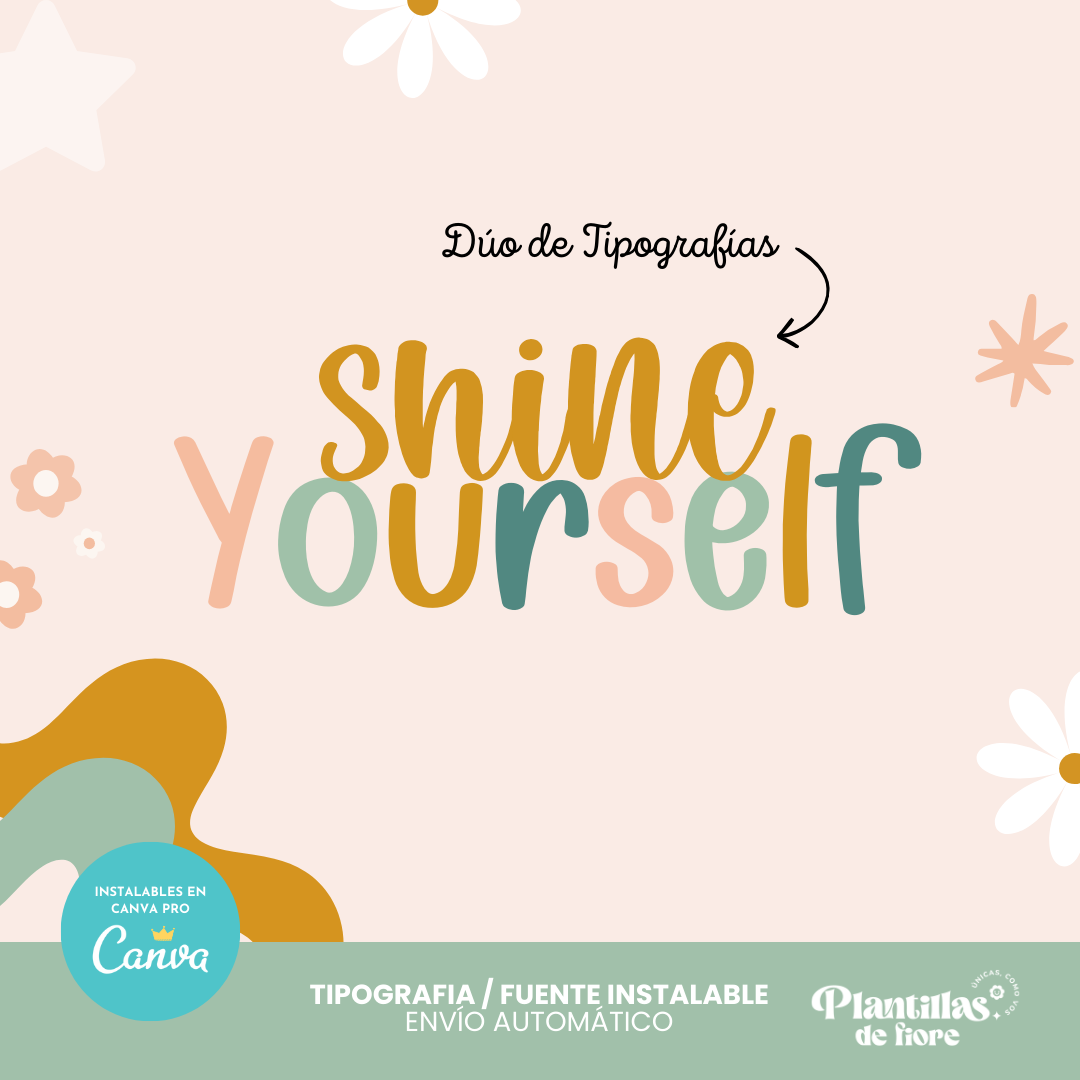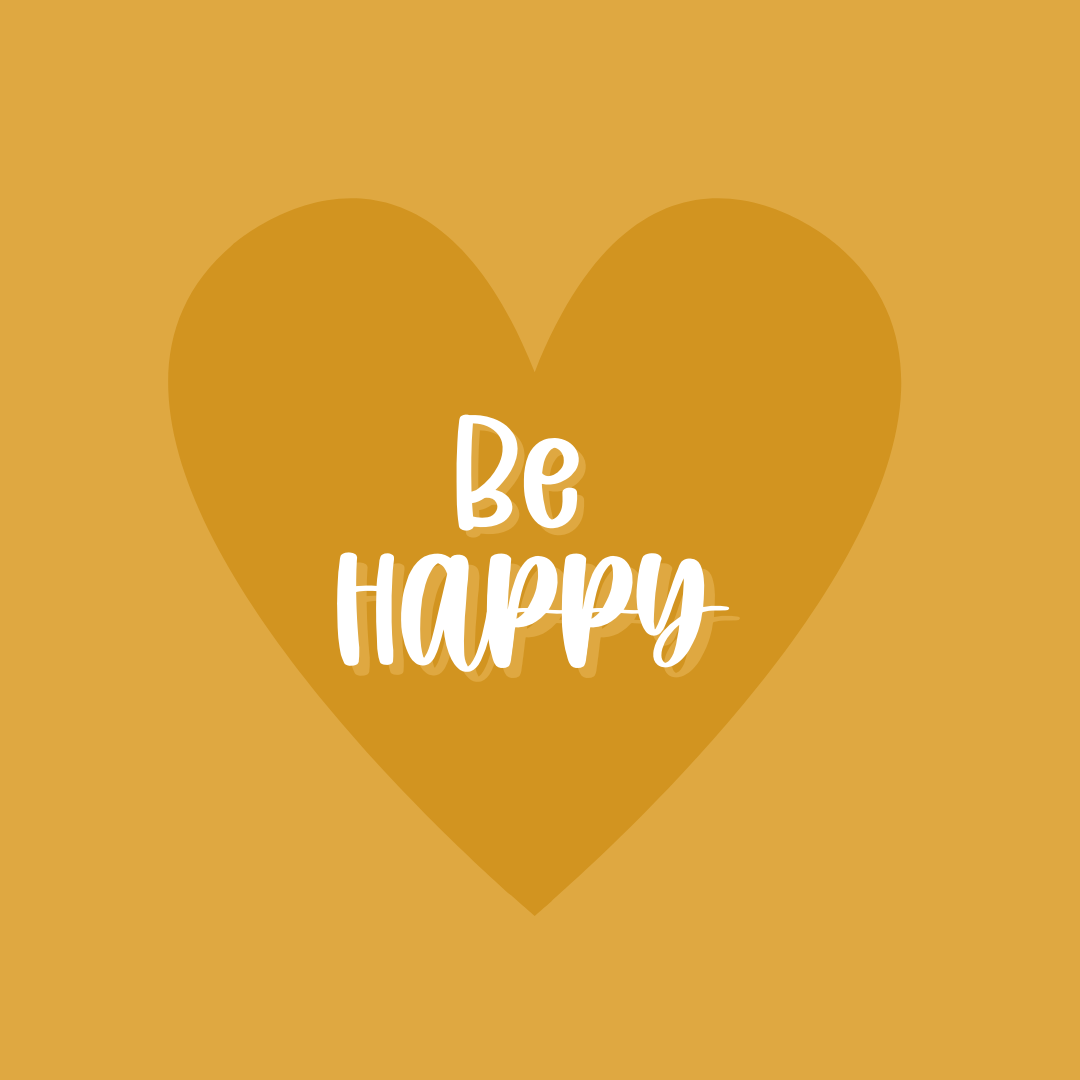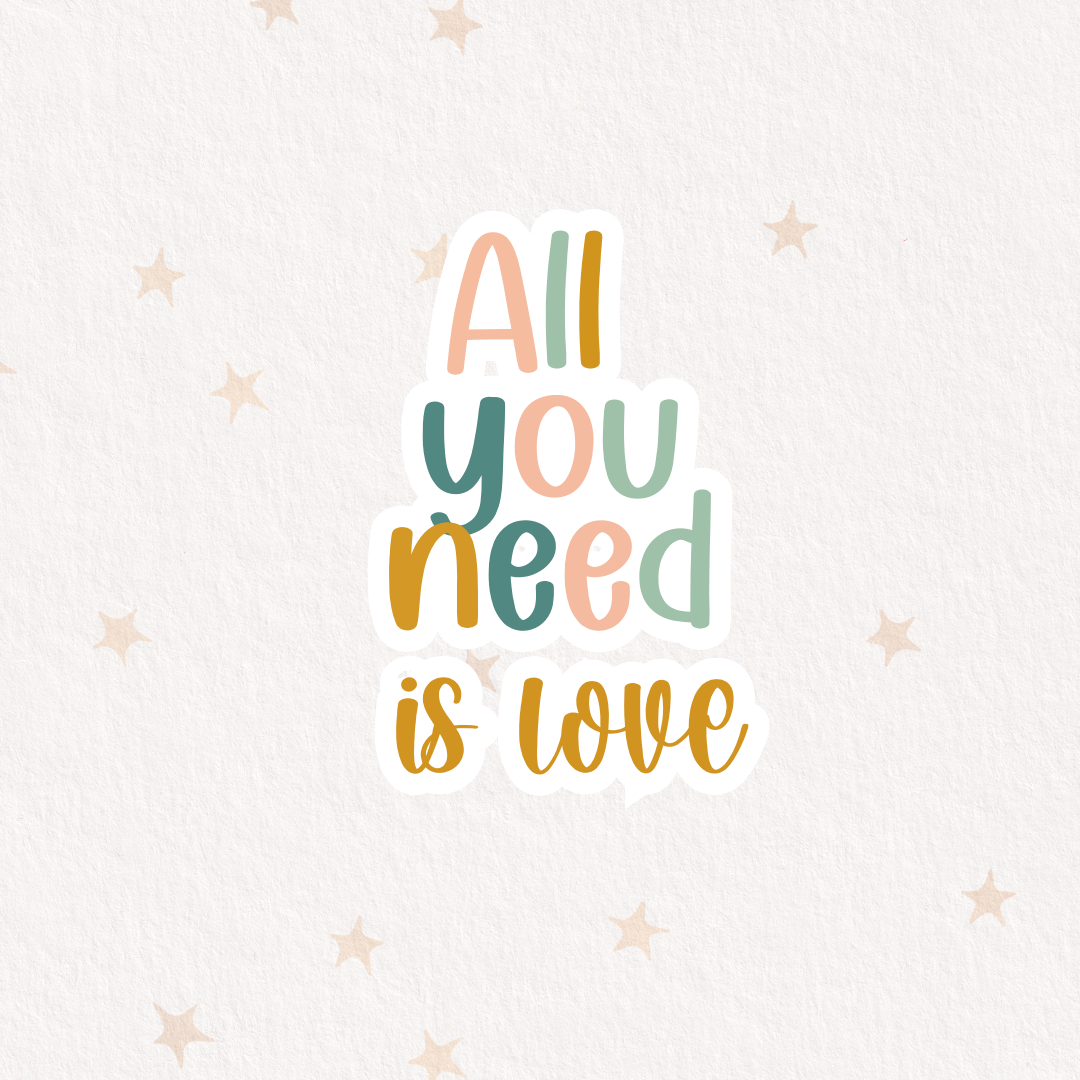
✨ Dúo de Tipografías Digitales Instalables – Combiná y creá sin límites
Recibí dos tipografías digitales instalables, pensadas para usarse juntas y lograr diseños armónicos, modernos y con estilo ✨